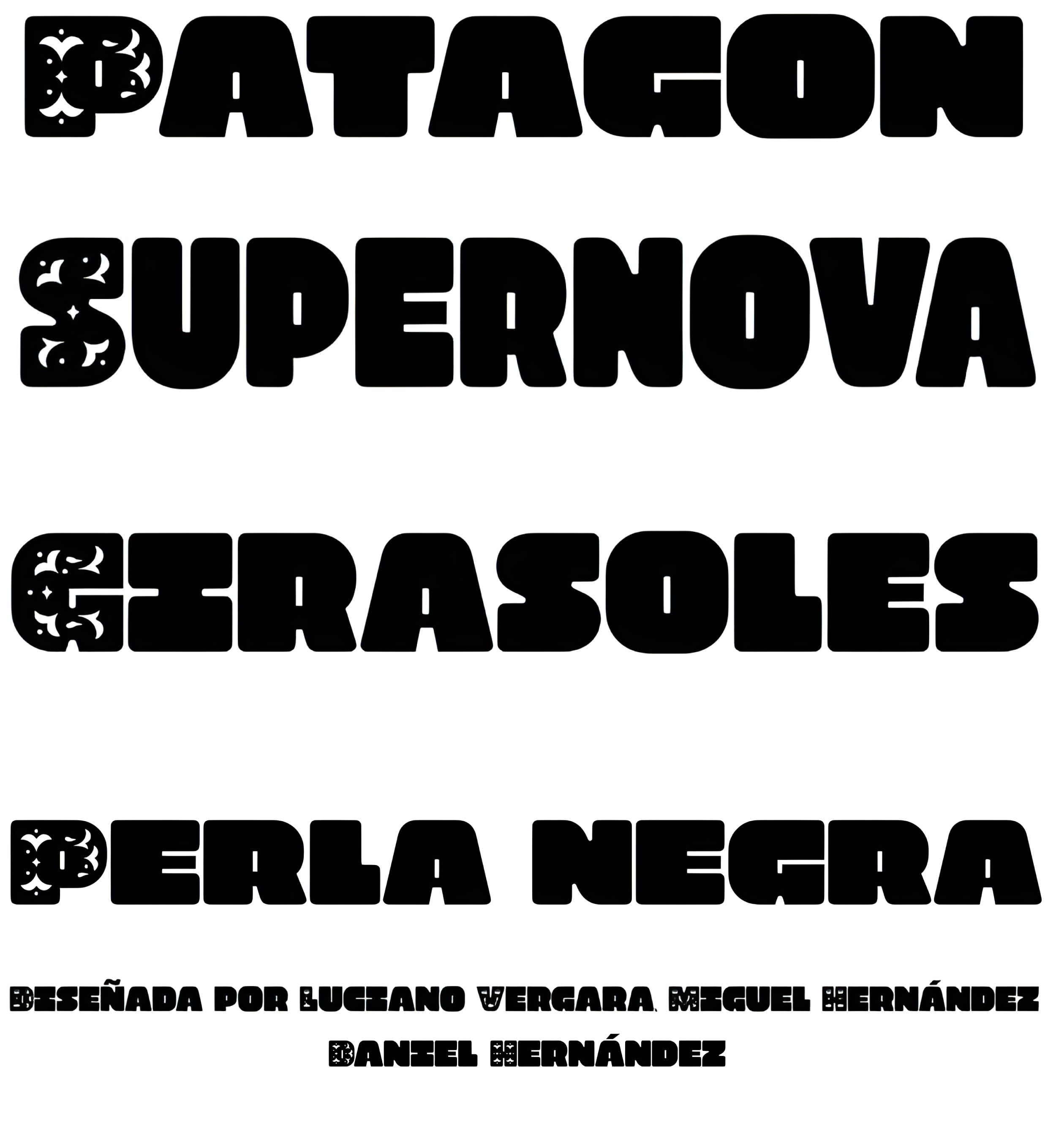
| Créditos | Luciano Vergara, Miguel Hernández, Daniel Hernández |
| Descripción | Patagon es un tipo de letra Woodtype Sans contemporáneo especialmente diseñado para frases frescas y de gran impacto con una mezcla de rasgos de sabor. Sus glifos alternativos ornamentales Opentype en mayúsculas proporcionan texturas elegantes que añaden versatilidad a la familia de tres pesos: condensado, normal y extendido. Combínelos para conseguir un diseño realmente atractivo. |
| Familia(s) | Condensed, Regular, Expanded |